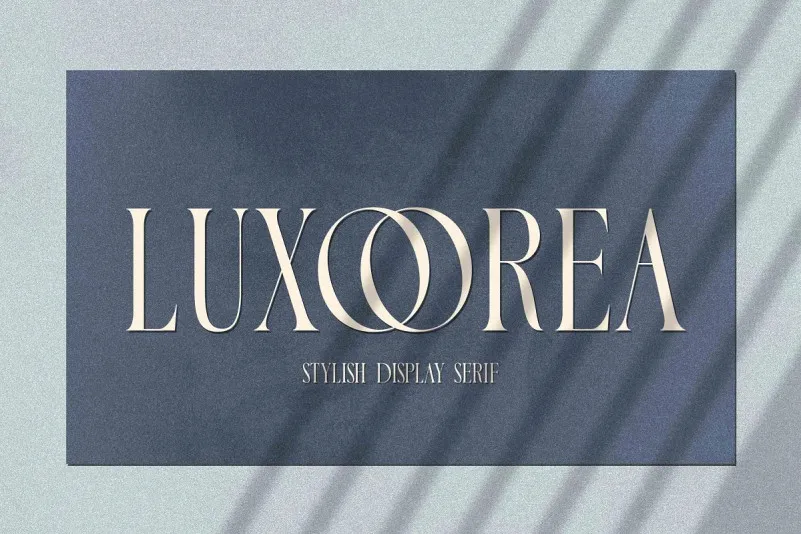
A Luxoorea Font é uma elegante tipografia serifada criada pela Almarkha Type, repleta de características sofisticadas que tornam-a perfeita para diversas aplicações digitais. Inspirada no famoso logotipo minimalista, esta fonte atende a um amplo espectro de necessidades de design, desde templates até brochuras, vídeos e embalagens publicitárias. Suas linhas sutis e arquitetura detalhada permitem uma apresentação gráfica sofisticada e envolvente, tornando-a ideal para ambientes de marca, logotipos e design de branding. Com a Luxoorea Font, você pode adicionar um toque refinado aos seus projetos digitais, transformando-os em verdadeiros produtos de alta qualidade.